一些非常不错的商用字体,做设计囤些好看的免费商用字体也是很很很有必要的!由于免费可商用的字体目前有很多,下面我只列出一小部份比较具有代表性的字体,剩余字体大家可自行前往字体视界免费下载
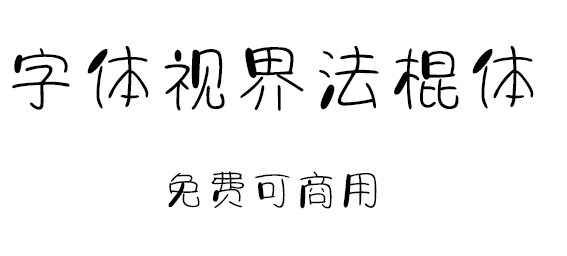
字体视界法棍体由字体视界推出的首款免费字体,它将免费开放商业授权给到所有个人和企业,让所有用户可以免费使用。
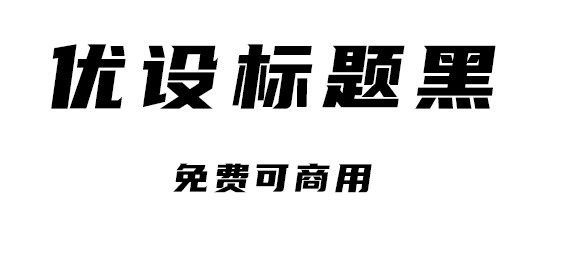
优设标题黑是一款适用性广,速度感、力量感极强的专业美术标题字体
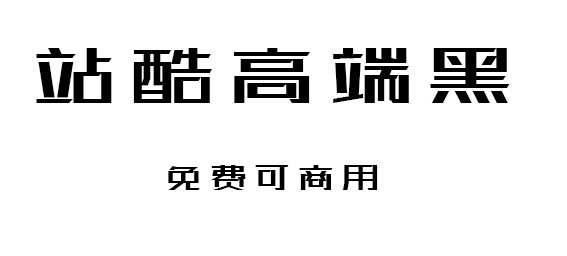
站酷高端黑是2014年圣诞发布的第一款由站酷冠名的公益字体,字体设计师胡晓波、刘兵克在站酷网发起“汉字百人舞”的征集设计师集体造字,前后参与设计师近百人。
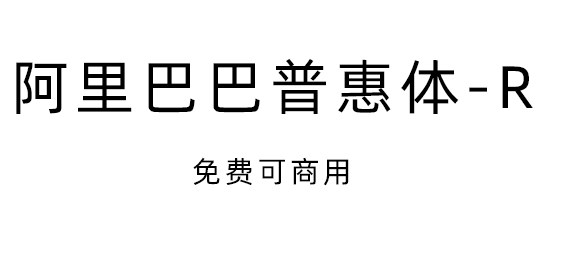
阿里巴巴普惠体-R不仅包含突显企业品牌个性的标题字体,还囊括了更为实用的内文字体,适合于一个场景下的多种应用